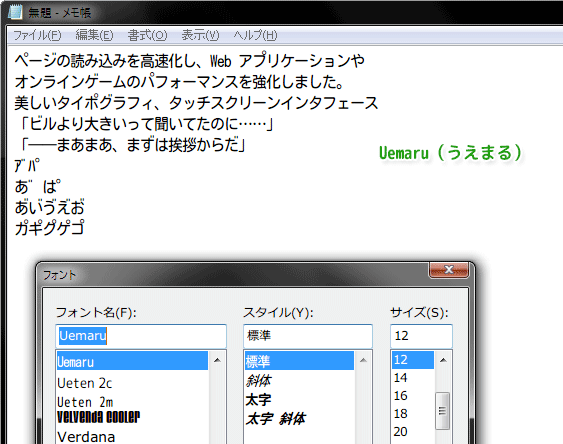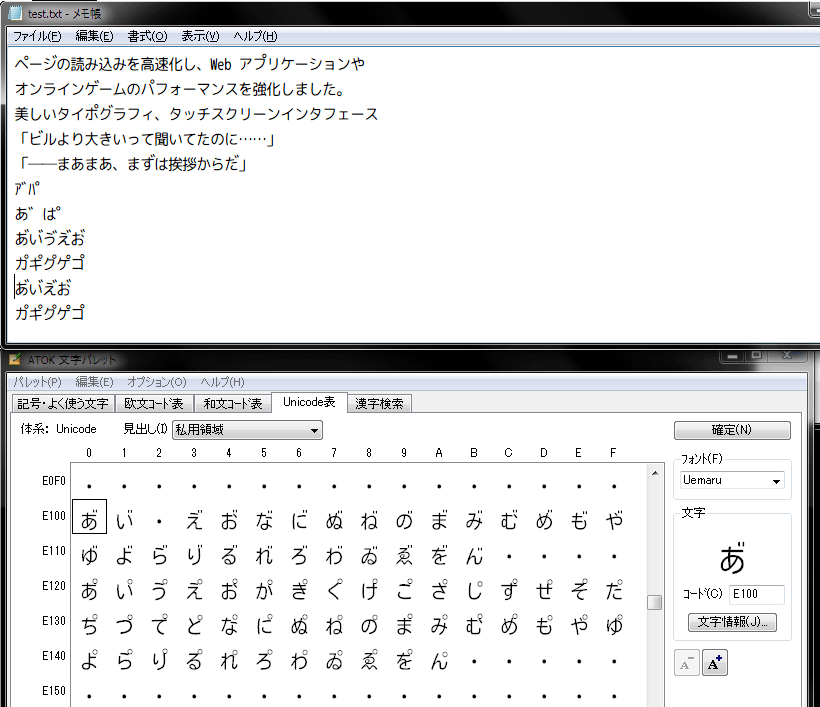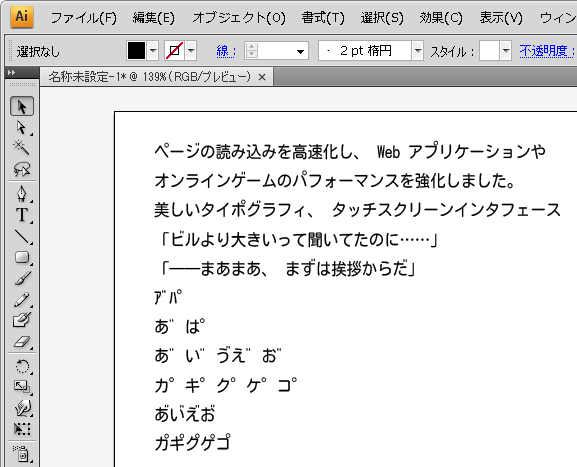
Uemaru(うえまる)フォントを作成したので公開します。
濁点・半濁点を文字の上に付けたTrueTypeアウトラインフォントです。
「モトヤLマルベリ3等幅」を改変しました。
Uetenフォントの姉妹フォントになります。
Uemaru(うえまる)フォントの特徴
- 丸ゴシックの等幅フォント。
- 少し縦長の字形。
- 濁点・半濁点は文字の上に付く。
- 半濁点が大きめ。
- JIS第1・第2水準の文字をすべて収録。
- 「モトヤLマルベリ3等幅」に存在しない記号をいくつか「M+ OUTLINE FONTS」から追加した。
- 「あ」+「゛」のような濁点・半濁点合成字形を収録。外字または合字として使用可能。
仕様:
- 縦書きに非対応。
- 濁点・半濁点合成字形は「合字としては」Adobe製品では使用不可。外字としては可能。
- ウェイト(太さ)はRegularしかない。
フォント名は「文字の上に半濁点(マル)をつける」ことから命名しました。
改変箇所
- 横幅を92%に縮小。つまり少し縦長の字形にした。
- 濁点・半濁点を文字の上に付ける。
- 存在しない記号をいくつか「M+ OUTLINE FONTS」から追加した。
- 「あ」+「゛」のような濁点・半濁点合成字形を追加。
- 「―」(U+2015 HORIZONTAL BAR)を横に伸ばした。
- U+005C をバックスラッシュ字形にした。
- 行幅(フォントの縦幅)を少し広くする。濁点・半濁点を上に置いたため。
Uetenフォントとの違い
Uetenフォント http://itouhiro.hatenablog.com/entry/20140502/font と同じ作り方で作成しています。見た目は似ていますが、以下が違います。
ページの読み込みを高速化し、Web アプリケーションや オンラインゲームのパフォーマンスを強化しました。 美しいタイポグラフィ、タッチスクリーンインタフェース 「ビルより大きいって聞いてたのに……」 「――まあまあ、まずは挨拶からだ」 ア゙パ あ゛は゜ あ゙い゙ゔえ゙お゙ カ゚キ゚ク゚ケ゚コ゚
合字/外字として使用
合字として使用
「あ U+3042」+「合成用濁点 U+3099」として入力。 http://itouhiro.hatenablog.com/entry/20140925/font などからコピーペーストするのが早いかも。
外字として使用
IME(ここではATOK2012)のUnicode文字パレットで、U+E100 以降の外字を入力。
外字としてならAdobe Illustratorなどでも表示可能。ゲームエンジンで使う場合も外字のほうが都合いいかも。
ところでこの外字表に「ゔ」がないのはなぜ?
「ゔ」は U+3094 に置くことになっている。そこを探せばあるよ。 参考: wikipedia:ヴ
外字ならどこでも一文字に見えるから、外字のほうがいいんじゃないの?
外字は「違うフォント」で見るとまったく表示されないという欠点があるよ。
ただし、このフォントの外字は、以下のフォントと同じ位置に同じ外字を置いてある。つまり以下のフォントなら同じ外字を使えるよ。
しかしそれ以外のフォントでは外字を表示できない。
合字なら未対応フォントでも、たとえば「あ U+3042」+「合成用濁点 U+3099」なら「あ」は表示される(合成用濁点は位置がずれたりもあるけど)。使用フォントを固定できる環境以外では、合字のほうが安全だな。
Uemaruフォント作成途中のフォントも収録。
MLMaruCircle(エムエル・マル・サークル)フォント
Uemaruフォントとの違い:
- 各文字の横幅を縮小していない。モトヤLマルベリ3等幅と同じ横幅。
- 行幅(フォントの縦幅)もモトヤLマルベリ3等幅と同じ。
- 濁点・半濁点は文字の上ではなく、モトヤLマルベリ3等幅と同じ位置にある。
- 「ぱぴぷぺぽパピプペポ」の半濁点が大きい(140%)。
- 「あ」+「゛」のような濁点・半濁点合成字形は収録していない。
仕様:
- 縦書きに非対応。
フォント名は「モトヤLマルベリ3等幅」の英語名「MotoyaLMaru」を多少変えました。 ウェイトが Regular ではなく「W3 mono」になっているのは、「モトヤLマルベリ3等幅」と同じです。